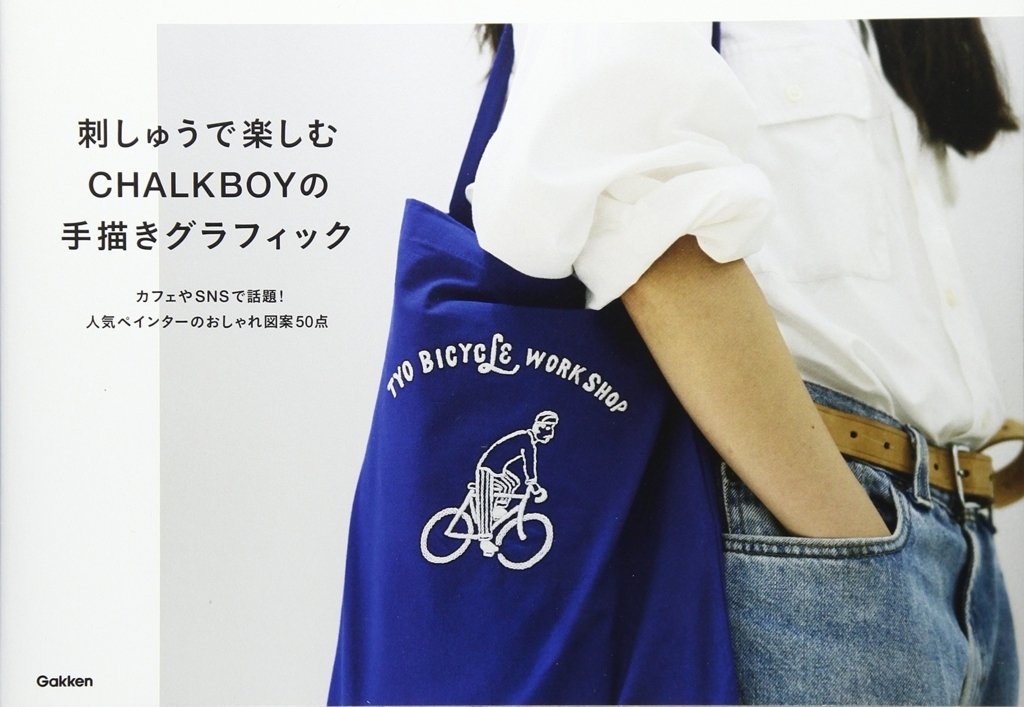
刺しゅうで楽しむ CHALKBOYの手描きグラフィック
ハンドレタリング作家として活躍中のCHALKBOYのお洒落な図案50点を使用した刺しゅう本「刺しゅうで楽しむ CHALKBOYの手描きグラフィック」が学研プラスから2017年11月14日に発売されている。
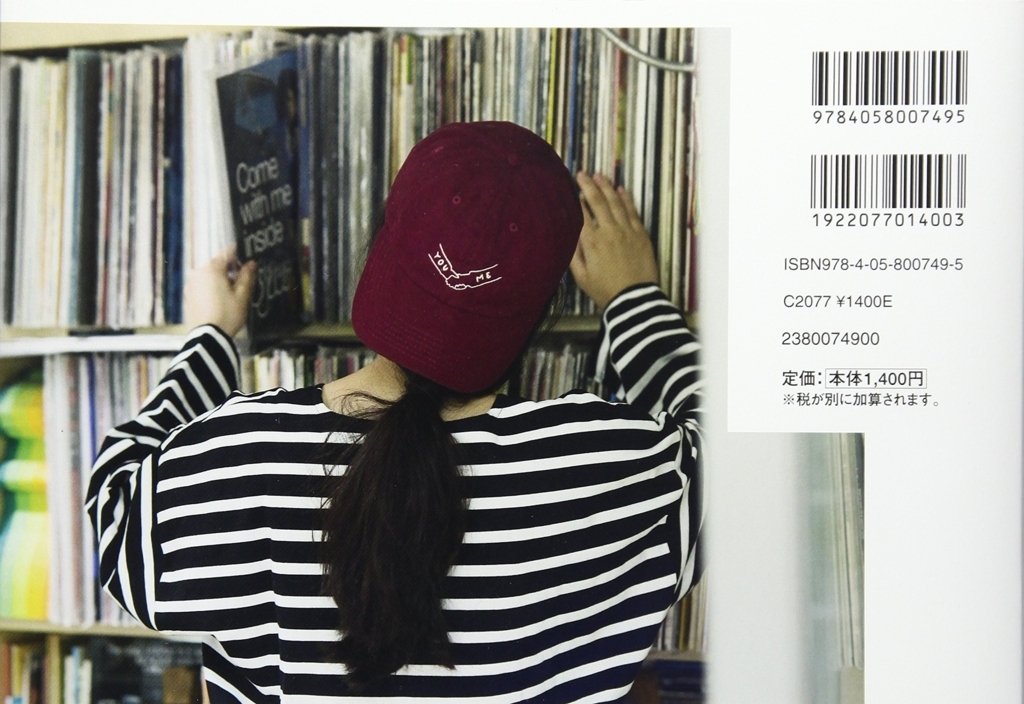
カフェやSNSで話題! 人気ペインターCHALKBOYのおしゃれ図案50点が刺しゅうに!
カフェやコーヒースタンドなど、あらゆる場所で目にするようになった、手描きグラフィック。本書は、ブームの火付け役でもある人気ペインターCHALKBOYの図案を使った刺しゅう本です。
本書で紹介している図案は、ワンポイントとして使えるシンプルなものばかり。
ステッチも、「アウトラインステッチ」や「サテンステッチ」、「チェーンステッチ」など基本的な刺し方が中心なので、刺しゅうははじめて、という人でも安心して楽しめます。
刺しゅうが少しゆがんだり、図案から糸がはみ出してしまったりしても大丈夫!
それは“手描き"の味わいそのものですから。
いつも着ているお気に入りのシャツに、シンプルすぎて味気なかったバッグやクロスに、大切な誰かへの贈り物に、、、ほんのちょっと、刺してみるのはいかがでしょうか。日常を少しだけ特別にしてくれること、間違いなしです。